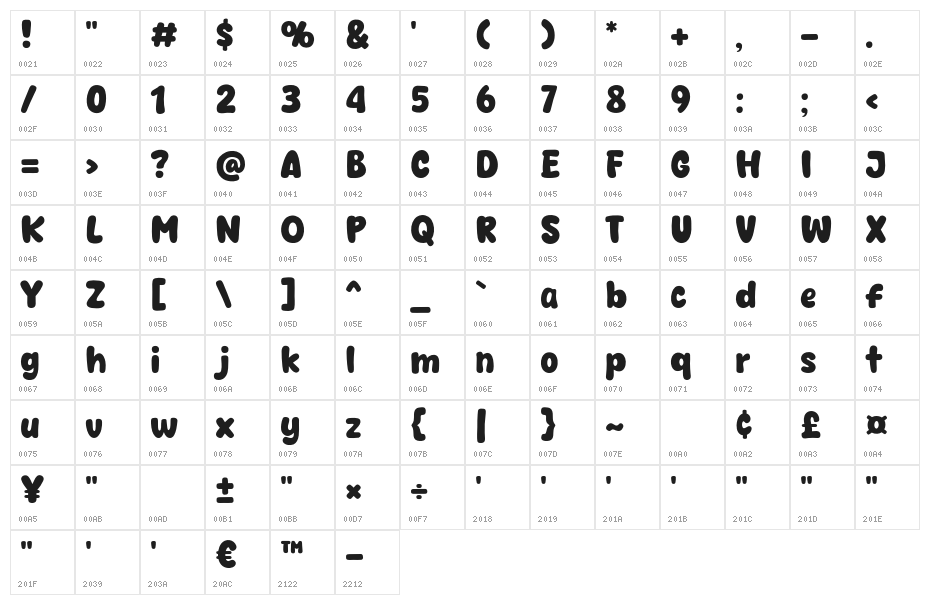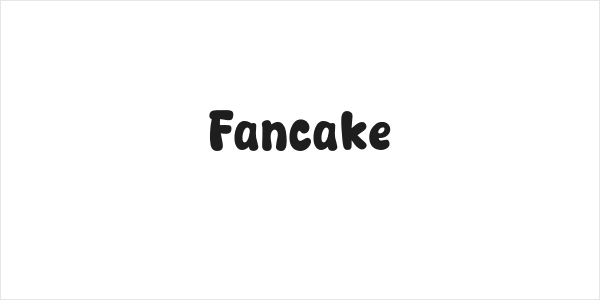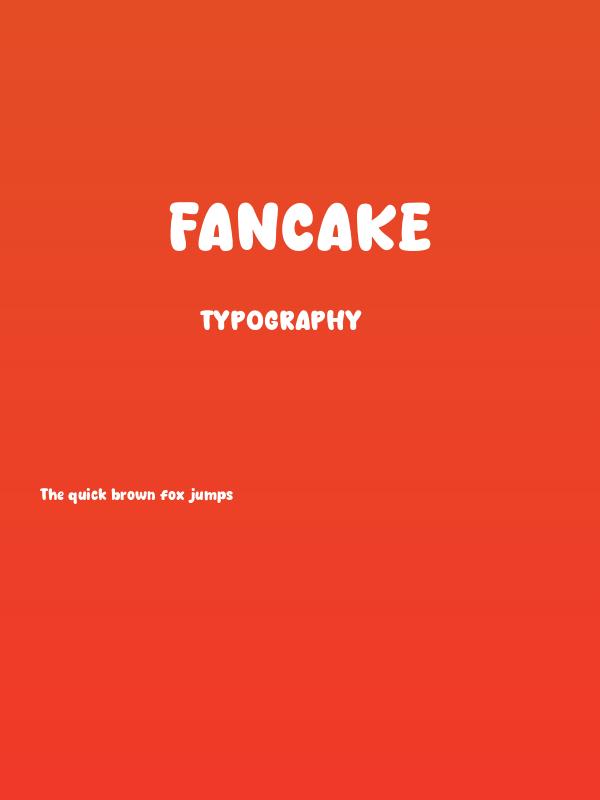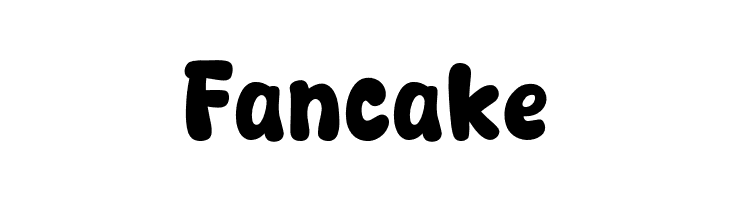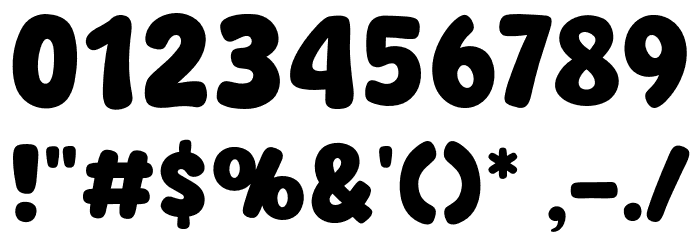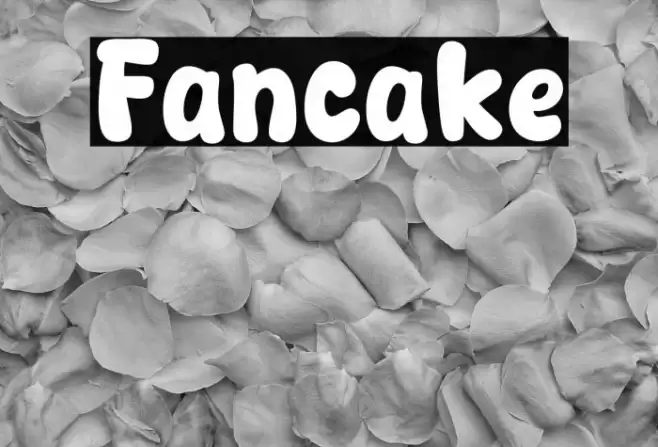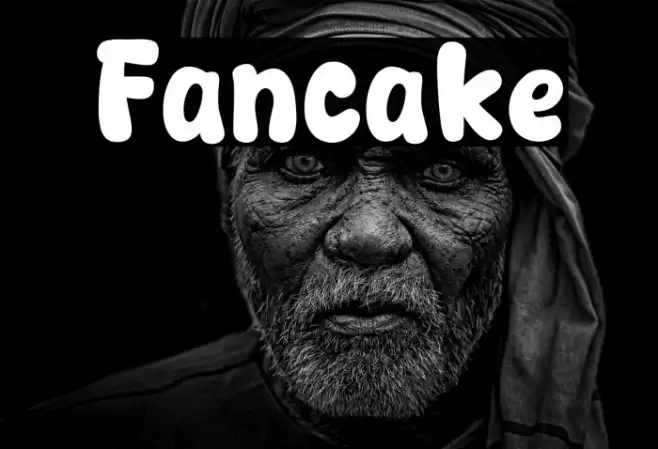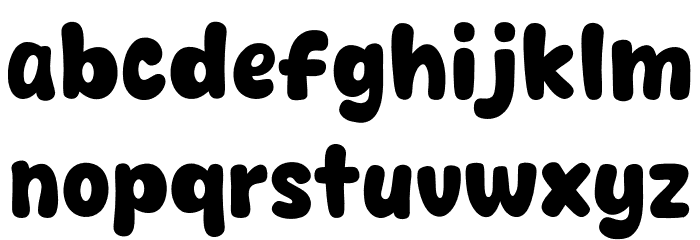
Fancake Font
| Estilo general | Playful |
| Caso de uso | Logos, Headlines, Posters |
| Proyectos propuestos | Ideal for children's books, playful branding, party invitations, and fun social media graphics. |